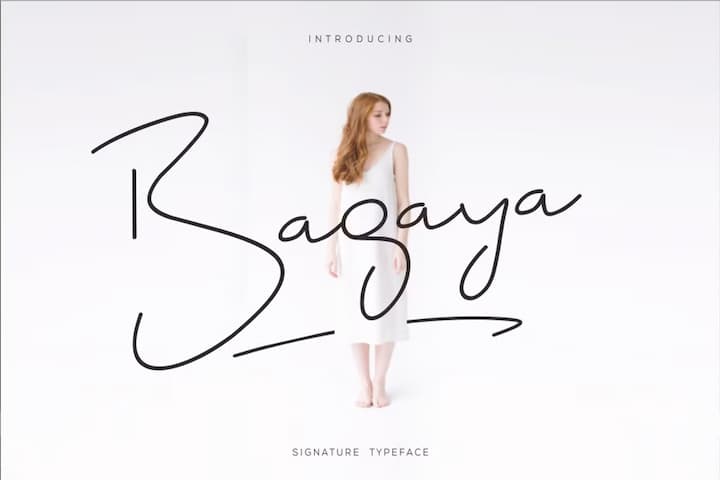
Bagaya
カジュアルでガーリーなシグネチャースクリプト。モノラインストロークでゆるゆるなグリフの書体で、大文字と小文字のサイズ比が大きくダイナミック。小文字の可読性は良好そうに見えて、n, m, u, v, w の区別がやや付きにくいが、まあスペルでなんとなく見当がついて読めると思う。残念なことにオルタネートがまったくなく、リガチャーもちょっとだけ。インドネシアとかあの辺の人が作る書体に多いが、hh や jj、rr といったどこで使うか分からないリガチャーがあったりする(向こうでは使う?)。1ウェイトのみ。